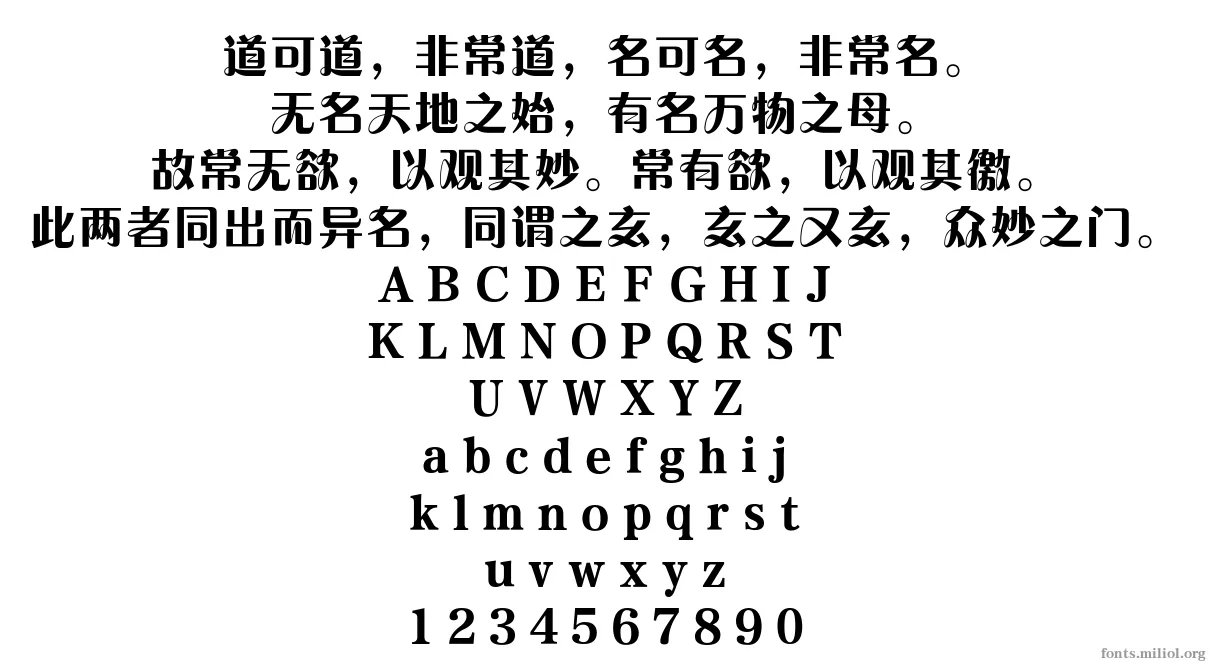
方正粗活意_GBK (FZCuHuoYi-M25) (FZCHYK--GBK1-0) 字体下载
《方正粗活意_GBK:传统美学与现代设计的交融》
方正粗活意_GBK(FZCuHuoYi-M25)是一款兼具传统书法韵味与现代设计感的字体,隶属于方正字库的经典GBK字符集产品。其名称中的“粗活意”暗示了字体风格——笔画粗犷有力,却又通过灵活的曲线传递出随性洒脱的意趣,特别适合需要突出文化底蕴与视觉张力的设计场景。
作为GBK编码字体,方正粗活意支持超过两万个汉字字符,涵盖简体、繁体及生僻字,能够满足出版、广告、品牌标识等多场景需求。其独特的笔触保留了毛笔书写的飞白与顿挫,但通过标准化设计确保了印刷与屏幕显示的清晰度,实现了艺术性与实用性的平衡。例如,在传统节日海报或文创产品中,这款字体能迅速营造出浓厚的中国风氛围;而在现代品牌包装上,又能以鲜明的个性脱颖而出。
尽管设计灵感源于手写体,但方正粗活意通过严谨的数字化处理,确保了笔画结构的稳定性,使其在小字号下仍保持可读性。这款字体不仅是设计师的工具,更是汉字美学在数字时代的生动延续。
方正粗活意_GBK 字体映射图